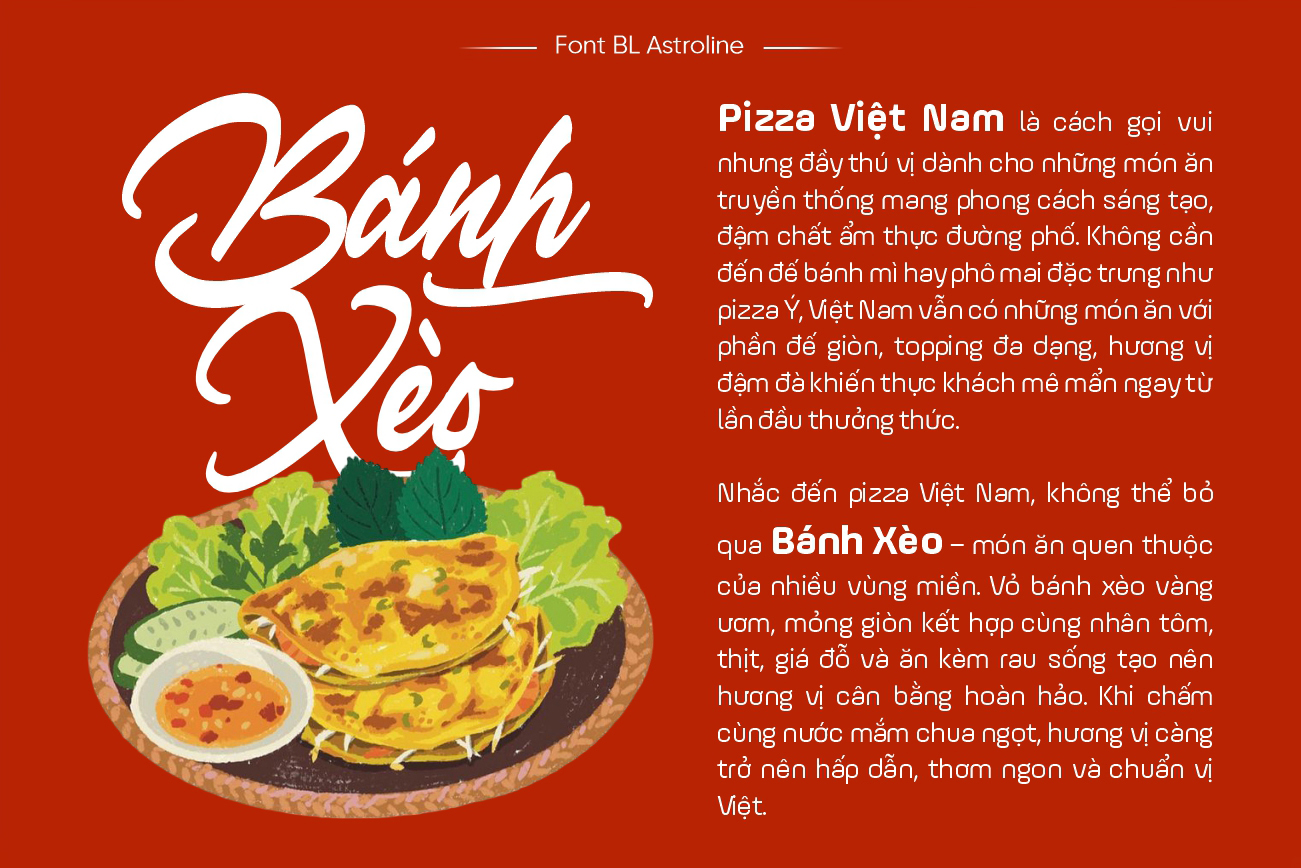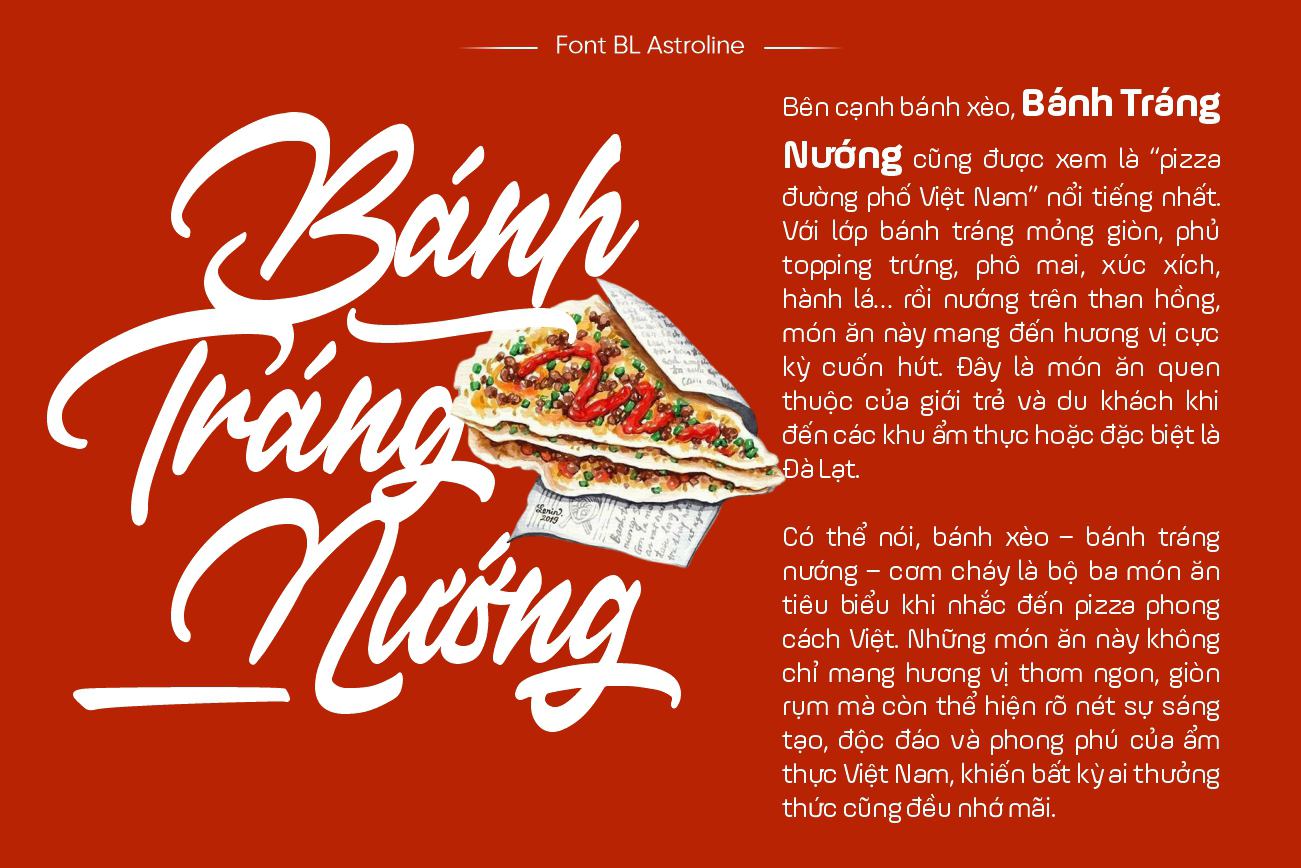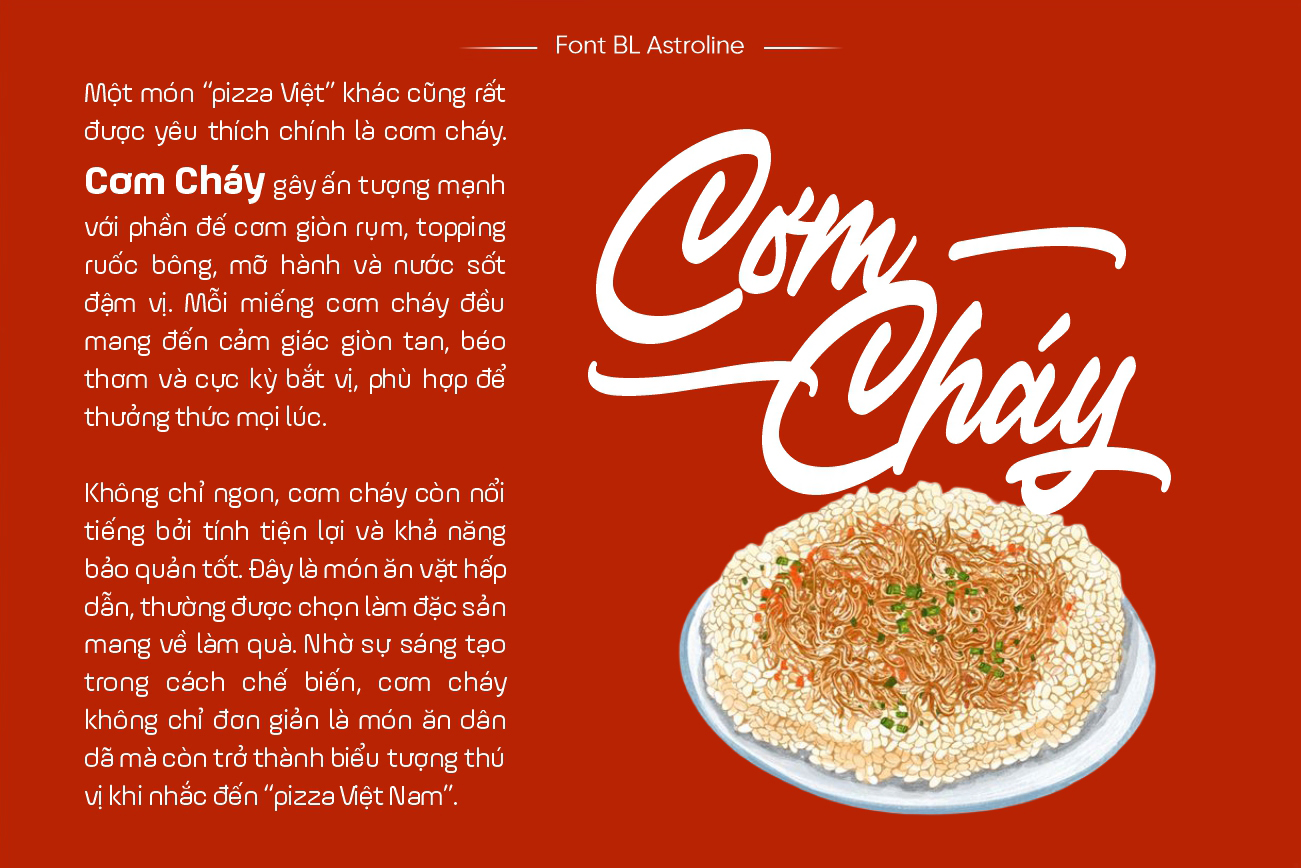
BL Astroline - Font brush với vẻ quyến rũ cổ điển
BL Astroline là phiên bản Việt hóa từ bộ font Astroline do Bangkit Tri Setiadi thiết kế, mang tinh thần nghệ thuật đầy cảm xúc với sự kết hợp hài hòa giữa nét cổ điển và sự hiện đại tinh gọn. Ngay từ cái nhìn đầu tiên, bộ chữ gây ấn tượng bởi phong thái của một font brush với vẻ quyến rũ cổ điển, gợi cảm giác mềm mại như những nét bút được vẽ bằng tay trên nền giấy, nhưng vẫn giữ được sự ổn định, chắc chắn trong bố cục. Team BL đã thực hiện Việt hóa BL Astroline một cách tỉ mỉ, tối ưu hệ thống dấu tiếng Việt một cách chính xác, đảm bảo sự uyển chuyển của từng ký tự được giữ nguyên mà vẫn phù hợp với thói quen đọc và sử dụng của người Việt, nhờ vậy font trở nên thân thiện hơn trong quá trình ứng dụng thực tế.
Về kiểu dáng, BL Astroline mang phong cách trung hòa giữa sự hoài cổ và chất đương đại. Những đường cong mềm mại, uyển chuyển tạo nên cảm giác gần gũi, tự nhiên, trong khi các nét chữ được xử lý gọn gàng, rõ ràng giúp font trở thành kiểu chữ viết tay hiện đại, sạch sẽ chứ không hề rối mắt hay khó đọc. Nhờ cấu trúc chữ giàu cảm xúc nhưng vẫn khoa học, BL Astroline phù hợp cho nhiều loại hình thiết kế, từ logo thương hiệu phong cách lãng mạn, poster nghệ thuật, bao bì sản phẩm, thiệp mời cho đến các thiết kế mang tính cá nhân hóa cao trên mạng xã hội. Sự mềm mại đan xen với độ chắc chắn tạo ra cảm giác quyến rũ thị giác, đúng tinh thần của một font brush với vẻ quyến rũ cổ điển nhưng vẫn đủ mới mẻ để đáp ứng nhu cầu thiết kế hiện đại.
Nguồn gốc cảm hứng của Astroline nằm ở tinh thần nghệ thuật viết tay, nơi chữ không chỉ để đọc mà còn để cảm nhận. Khi trở thành BL Astroline, bộ font tiếp tục phát huy tinh thần đó nhưng được nâng cấp để phù hợp với tiếng Việt và môi trường sáng tạo Việt Nam. Đây là lựa chọn lý tưởng cho những nhà thiết kế, thương hiệu hoặc cá nhân đang tìm kiếm một bộ chữ vừa mềm mại, giàu cảm xúc, vừa mang tính thẩm mỹ cao và giữ được sự gọn gàng, dễ đọc của một kiểu chữ viết tay hiện đại, sạch sẽ.
Nếu bạn cần một bộ chữ mang đậm cảm xúc nghệ thuật nhưng vẫn đảm bảo tính ứng dụng thực tế, BL Astroline chắc chắn sẽ là lựa chọn đáng trải nghiệm, giúp thiết kế trở nên tinh tế, cuốn hút và giàu tính biểu cảm hơn bao giờ hết.